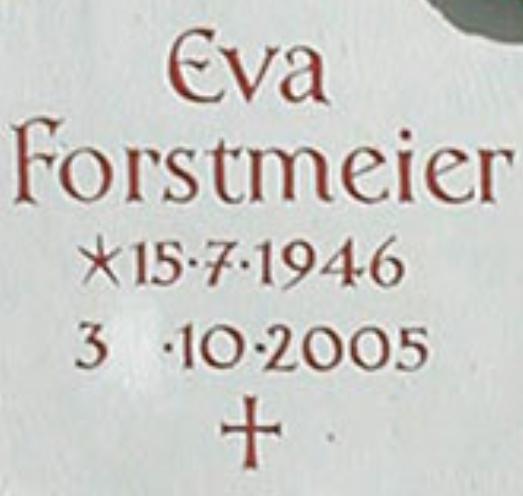
Suche Schrift von dieser Tafel
für eine neue Tafel suche ich diese Schrift. Drei Stunden Internet-Suche hat leider nicht gebracht... jetzt hoffe ich sehr, dass ihr mir weiter helfen könnt.
Generell kan man sagen, dass Steinmetzt nicht selten die Vorlage für spätere Deuckschriften lieferten, waren deren Beschriftungen ja für eoine lange Zeit bestimmt. Daher gehörte Schriftgestaltung zu deren Ausbildung, und jeder Steinmetzbetrieb hatte in vordigitaler zeit einen Schatz an Entwürfen, die über generationen gesammelt und gepflegt wurden. Das warem immer schon schriften, die es dann nicht als Satzschridften zum Druck gab, aber eben nicht selten dafür die Vorlage lieferte,. Bekannte Beispiele sind die Insxchriften der Römischen Trajanssäule, die Vorlage für praktisch alle Antiquaschridften, oder die von Herman Zapf entdeckte Vorlage der Optima.
Auch hier hast du es mit einer Arbeit eines unbekannten Steinmetz-Meisters zu tun. Nicht selten sind solxche Schriften auch nur örtlich präsent, und füllen da die Grabsteine des Ortes über Generationen, während in einiger Entfernung von den dortigen Handwerkern bestimmte Grundschriften, wie Antiqua oder Unziale auch wieder anders interpretiert wurden. Für Schriftgestalter, die dann Schridften für den Druck zeichnen, optimoeren und in Stempel für den Letternguß schnitten, bzw für heutige digitale Schriftentwerfer, wie die Herren Stötzner, Weiß, Herrmann und aauch mich (und einige andere stehen da oft wahre Schätze in Stein gehauen, die darauf warten, zur Druckschrift zu werden. Nur umgekehrt, nahezu alles, was älter als etwa 30 Jahre ist, und nixcht auf Papier gedruckt ist, waren zumeist keine benannten Druckschriften, da es für alle Handwerke, egal ob Schilder- und Reklamemaler, Lackierer, die Fahrzeuge beschrifteten, oder eben Steinmetze viel zu zeitraubend war, sich ihre Texte erst einmal in einer Setzerei oder Druckerei setzen und abziehen zu lassen, um diese dann doch noch einmal nchzeichnen zu müssen. Da gehörte es zum einen eben zur Ausbildung, selbst für Schauwerbegestalter, aka Schaufenster-Dekorateuren einfach zum Berufsbild, und damit zur Ausbildung, Texte und Schriften zu entwerfen. Und manche von ihnen prägten lange noch das Bild der Städte mit ihrem persönlichen Schriftenstil. Das galt auch für Hersteller von Leuchtreklame.
wenn ich mir den Buchstaben »e« genauer ansehen, dann fällt auf, dass diese ungleich sind. Was ich mir vorstellen kann ist, dass der Steinmetz auf den Stein die Buchstaben mittels einer Druckvorlage (mit Kohlepapier) aufgebracht und dann gemeißelt hat. Demnach könnte eine digitalisierte Schrift als Ausgang gedient haben.